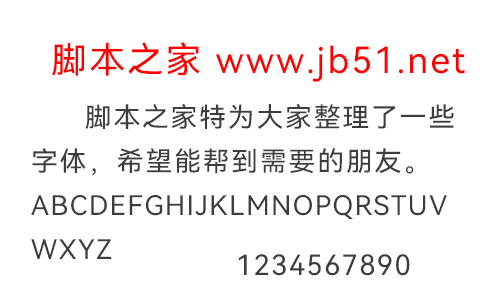
鴻蒙HarmonyOS字體是由華為發(fā)布的一套字體,通過研究用戶在不同場景下對多終端設備的閱讀反饋,綜合考量不同設備的尺寸、使用場景等因素,同時也考慮用戶使用設備時因視距、視角的差異帶來的字體大小和字重的不同訴求,我們?yōu)?HarmonyOS 設計了全新系統(tǒng)默認的字體——HarmonyOS Sans。歡迎喜歡此字體的朋友前來下載使用。